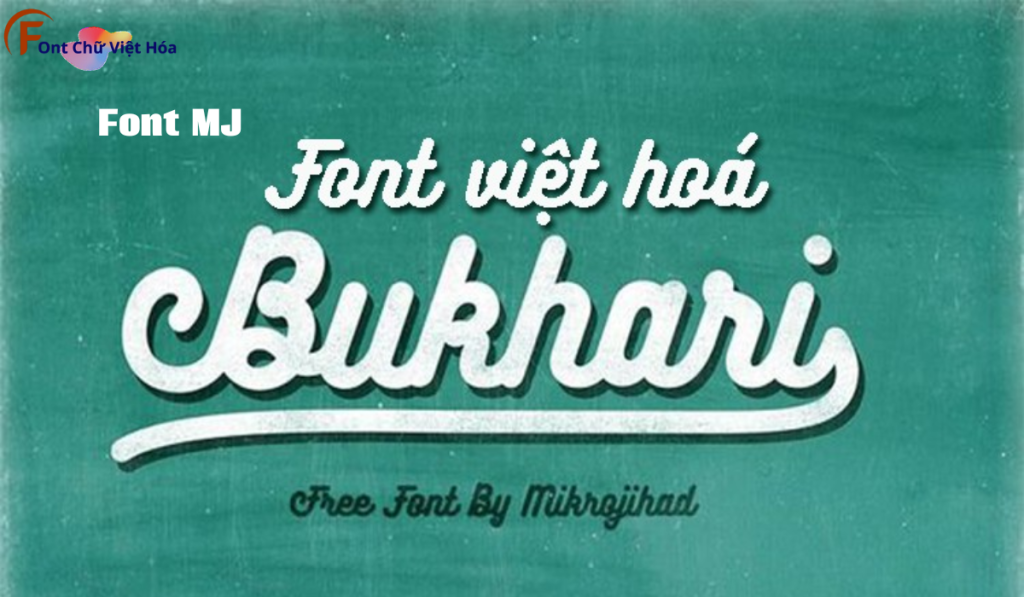
Font MJ Bukhari Script Việt Hóa
Tác giả: MJ Design
Bộ Font: MJ
Phân loại: Cá tính, Độc đáo
Kiểu chữ: Chữ viết tay
Font MJ Bukhari Script Việt Hóa là một font chữ viết tay cá tính, thuộc bộ font MJ. Được thiết kế với mục tiêu mang lại sự mềm mại và thanh thoát, font này lý tưởng cho các dự án thiết kế như thiệp mời, logo, và bao bì sản phẩm. Với các nét chữ uyển chuyển và độ dày đều đặn, Font MJ Bukhari Script Việt Hóa không chỉ dễ đọc mà còn tạo cảm giác thân thiện và gần gũi. Việc Việt hóa font giúp người dùng dễ dàng sử dụng trong các thiết kế tiếng Việt, mang lại sự tiện lợi và thẩm mỹ cao.